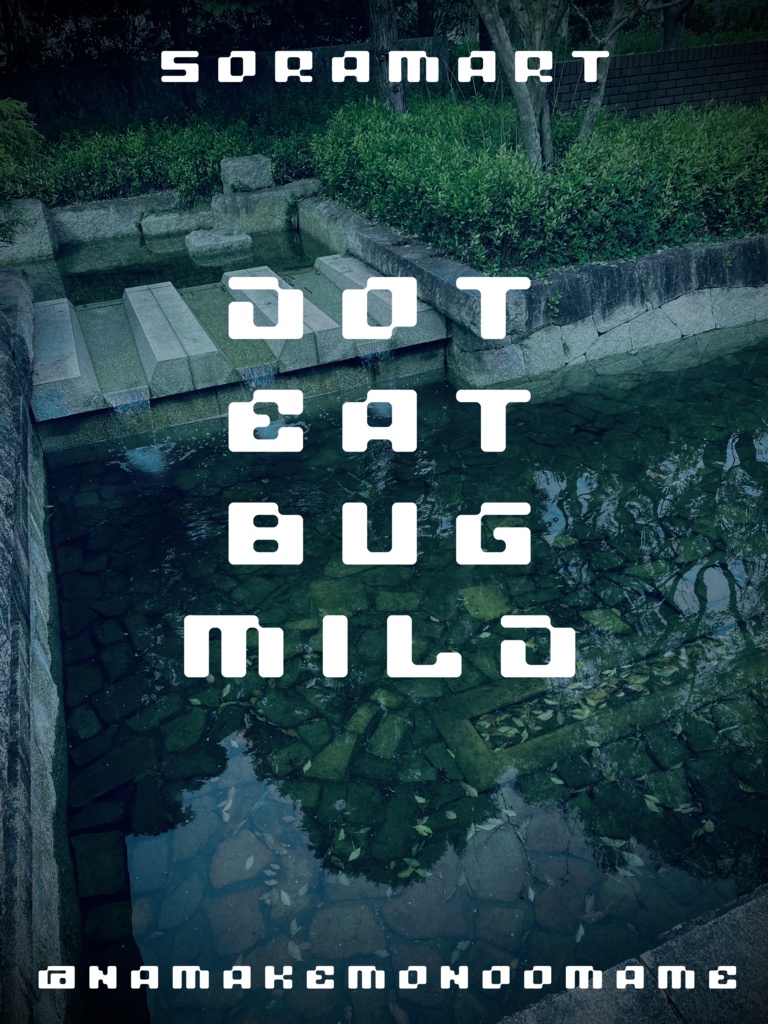
そらマートフォントデータ”Dot Eat Bug Mild”Digital2,500 JPY加入购物车Buy a GiftAbout Gift”バグ”をイメージしたドット調フォントに丸みをつけるアレンジを施した "Dot Eat Bug Mild" です。 「TrueTypeフォントファイル」という形式です。 ダウンロードした後、Zipファイル内のデータをインストールしてお使いください。 このフォントは商用利用可となっております。 お客様の制作・創作活動のお役に立てれば幸いです。 ※使用上の注意事項などは、添付のReadmeをお読みください。そらマートVisit FANBOX!Fontsフォントデータ”RANMMA Drive”そらマート0 JPYFontsフォントデータ”Dandy Laser Max”そらマート2,500 JPYFontsフォントデータ”Dandy Laser”そらマート2,500 JPYFontsフォントデータ”Bubblegum Beat”そらマート2,500 JPYFontsフォントデータ”Caltrop Serif LLL”そらマート2,500 JPYFontsフォントデータ”Caltrop Serif LL”そらマート2,500 JPYFontsフォントデータ”Caltrop Serif”そらマート2,500 JPYFontsフォントデータ”Tonik Crate Super Long”そらマート2,500 JPYFontsフォントデータ”Dot Eat Bug Acid”そらマート2,500 JPYFontsフォントデータ”Dot Eat Bug”そらマート2,500 JPYFontsフォントデータ”Solid Voltage Strike”そらマート2,500 JPYFontsフォントデータ”Solid Voltage”そらマート2,500 JPYFontsフォントデータ”Henge Edge Rock”そらマート2,500 JPYFontsフォントデータ”Henge Edge Tall”そらマート0 JPYFontsフォントデータ”Henge Edge”そらマート0 JPYFontsフォントデータ”Chisel Stroke Wide”そらマート2,500 JPYFontsフォントデータ”Chisel Stroke”そらマート2,500 JPYFontsフォントデータ”Crushed Can Serif Empty”そらマート2,500 JPYFontsフォントデータ”Crushed Can Serif Wide”そらマート2,500 JPYFontsフォントデータ”Crushed Can Serif”そらマート2,500 JPY查看更多